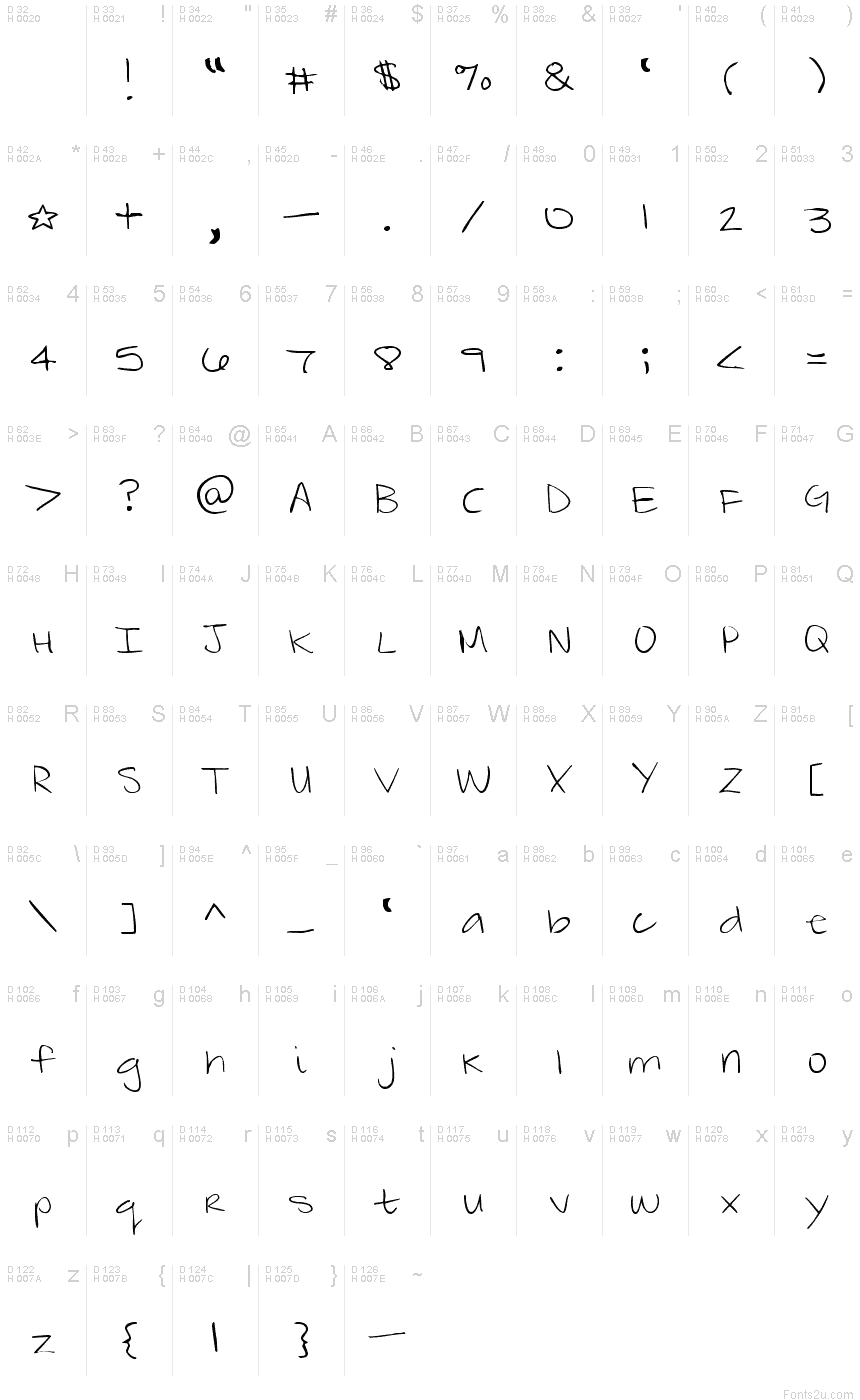
Zebra Flames Light, przypisana FontParty.com, to darmowy monolinearny krój pisma odręcznego o luźnej, szybko naszkicowanej budowie. Cienkie linie przechodzą między długimi, kanciastymi zamachami a zaokrąglonymi pętlami, nadając literom otwartą sylwetkę i nieregularny ruch swobodnego pisma odręcznego.
Projektowanie wydawnicze może wykorzystać ten krój do osobistych nagłówków okładkowych lub nieformalnych cytatów, zwłaszcza w artykułach poświęconych pamiętnikom, podróżom lub twórczości. Nadaje się również do papeterii, brandingu modowego i grafik cyfrowych, gdy projekt wymaga pisma odręcznego, które jest wyraziste, ale niezbyt ozdobne. Jego najbardziej przekonującą rolą jest wniesienie bezpośredniego, osobistego głosu do tekstu redakcyjnego.
Mapa znaków czcionki ZebraFlames Light